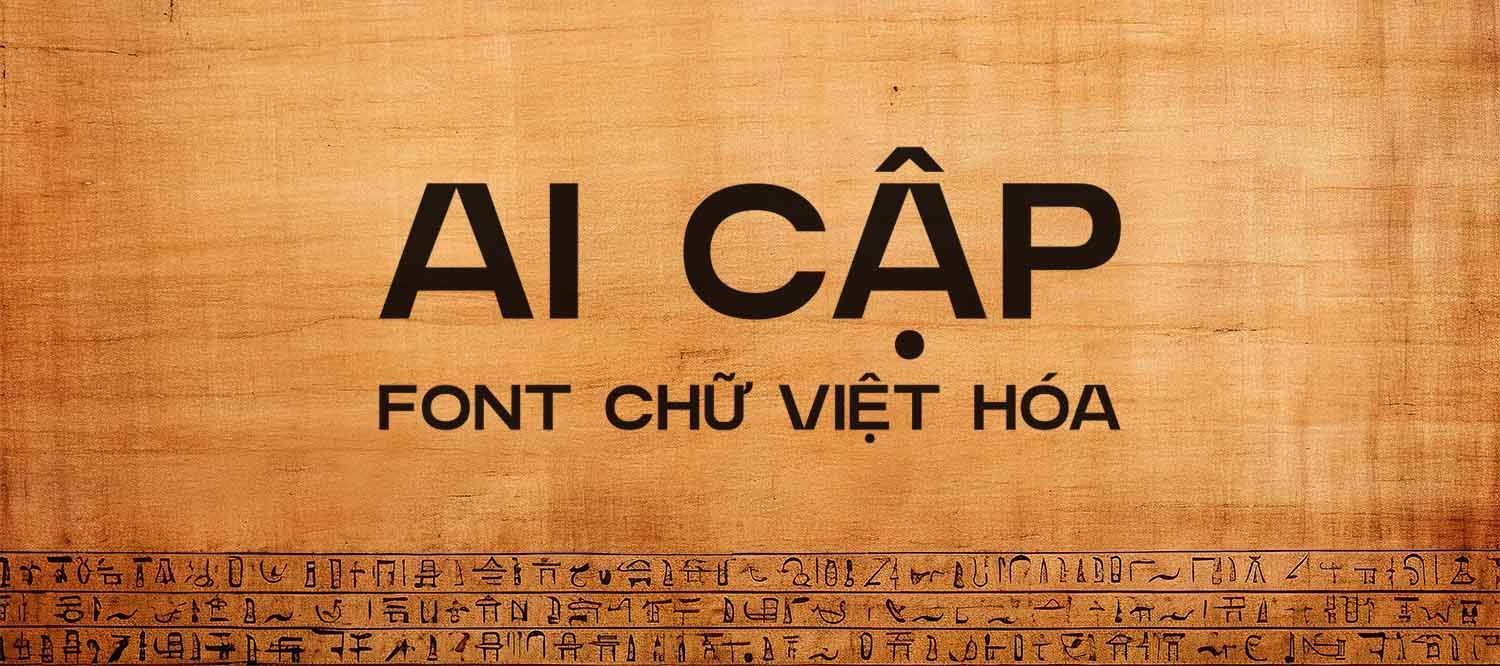
![[Tải Xuống] 8 Font Chữ Ai Cập Việt Hóa Mới Nhất 2025](https://cdn.s99.vn//cloud/Ybaxaa0q71KRf4B-.jpeg)
Font chữ Ai Cập là nhóm font lấy cảm hứng từ văn minh Ai Cập cổ đại, nơi nổi tiếng với hệ thống chữ tượng hình (hieroglyphics), hình khối mạnh mẽ, và những hoa văn trang trí đậm tính biểu tượng. Trong thiết kế hiện đại, font kiểu Ai Cập thường mang nét trang trí cổ kính, uy nghi và huyền bí.
Cũng cần phân biệt rõ với thuật ngữ “Egyptian” trong ngành typography, vốn là tên gọi khác của slab serif, kiểu chữ có chân vuông và dày, không nhất thiết liên quan đến Ai Cập về mặt văn hóa. Trong bài viết này, “font chữ Ai Cập” được hiểu là các font gợi nhắc đến nét đẹp cổ đại Ai Cập, đã được Việt hóa để dùng trong thiết kế tiếng Việt.
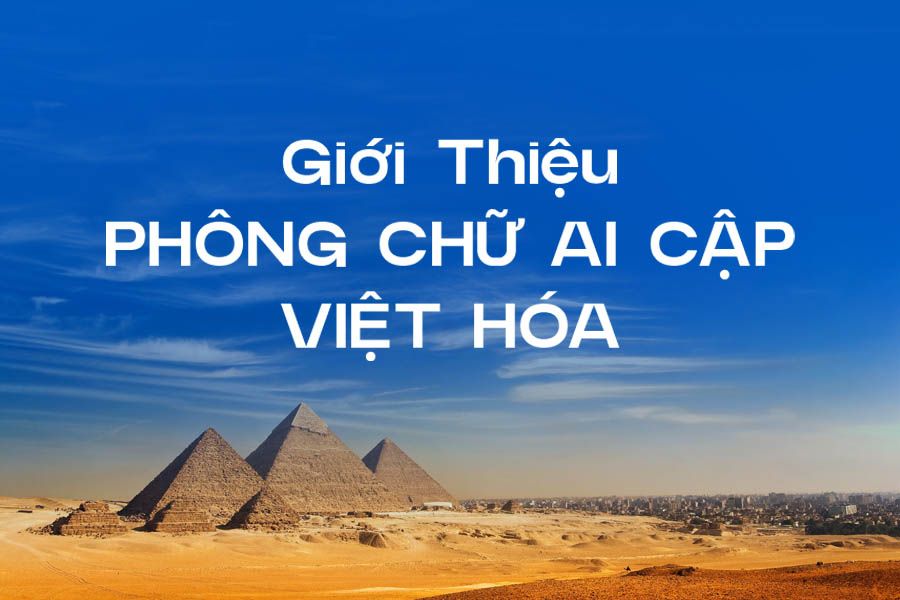
Nếu bạn đang tìm kiếm các font chữ Ai Cập Việt hóa mang đậm cảm hứng cổ đại, phù hợp để sử dụng trong các thiết kế poster lịch sử, sách cổ, game huyền thoại hoặc các dự án branding phong cách văn minh xưa – dưới đây là 8 lựa chọn font miễn phí, đã được Việt hóa hoàn chỉnh cho năm 2025.
Mô tả: SVN Nubya là font display mang phong cách font chữ Ai Cập hiện đại, với các đường nét đậm – mảnh tương phản, gợi cảm giác thư pháp Ả Rập cổ. Kiểu dáng uy nghi và phóng khoáng tạo nên một tổng thể bí ẩn, mạnh mẽ, rất phù hợp cho tiêu đề poster cổ đại, ấn phẩm tôn giáo hoặc các dự án thiết kế mang màu sắc thần thoại.
Mô tả: Tuy có tên gốc là Nhật Bản, font này khi Việt hóa lại sở hữu bố cục vuông vức, đều đặn, mang nét chạm khắc gỗ truyền thống – tương đồng với nhiều yếu tố tạo hình trong font chữ Ai Cập cổ đại. Đây là lựa chọn phù hợp cho các thiết kế phục dựng văn minh phương Đông, hoặc kết hợp trong các dự án lịch sử giả tưởng.
Mô tả: TH Lịch Sử 2 là font slab serif mạnh mẽ, thiết kế dựa trên hình khối vững chắc và cấu trúc chữ cổ điển, dễ gợi liên tưởng đến kiến trúc Ai Cập như kim tự tháp, tượng thần. Đây là một trong những font chữ Ai Cập Việt hóa lý tưởng cho các dự án game lịch sử, bìa sách khảo cổ hoặc các ấn phẩm bảo tàng.
Mô tả: Với đường nét sắc sảo và thanh mảnh, MTD Briliants Typeface tái hiện tinh thần vương giả, uy nghiêm trong các lăng mộ hoàng gia Ai Cập. Kiểu chữ cao, đầu nét nhọn nhẹ và thân chữ thanh thoát làm cho nó trở thành font chữ Ai Cập cao cấp, thích hợp với thiết kế logo, thiệp mời sang trọng hoặc bìa sách cổ tích huyền bí.
Mô tả: LNTH Daybreaker mang hơi thở của chữ khắc đá, nét đứt đoạn mô phỏng kỹ thuật khắc gỗ cổ xưa. Dù lấy cảm hứng từ lễ hội phương Đông, nhưng nhờ kết cấu chữ cổ và hình thái thủ công, font này vẫn rất phù hợp khi dùng như một font chữ Ai Cập cách điệu trong các thiết kế dân gian, cổ tích hoặc game thần thoại.
Mô tả: SVN Bestagrach là font serif có độ tương phản vừa phải giữa các nét, tạo nên cảm giác sang trọng như một bản khắc đá quý tộc thời Ai Cập cổ. Đây là font tuyệt vời cho các thương hiệu cao cấp muốn kết hợp yếu tố font chữ Ai Cập hiện đại vào bộ nhận diện thương hiệu.
Mô tả: Với thân chữ vuông, chân chữ to bản và các nét ngang dày, TH Juggernaut mang lại cảm giác của tấm bia khắc đá khổng lồ trong các ngôi đền Ai Cập. Đây là một trong những font chữ Ai Cập Việt hóa phù hợp nhất để dùng trong tiêu đề, poster hoặc giao diện cổ điển mang màu sắc thần thoại.
Tác giả gốc: Pixel Surplus
Việt hóa: S99.vn
Mô tả: TH Sawadikap là font trang trí có nét uốn mềm mại và chi tiết cong nhẹ ở đầu chữ, tuy lấy cảm hứng từ kiểu Thái cổ, nhưng nhờ yếu tố tạo hình tương tự chữ tượng hình và hoạ tiết Ai Cập, nó hoàn toàn có thể sử dụng như một font chữ Ai Cập biến tấu trong các thiết kế cổ tích, truyền thống, hoặc văn hóa giả tưởng.
Tác giả gốc: Naulicrea
Việt hóa: S99.vn
Mỗi font đều mang trong mình một câu chuyện thị giác: có font tái hiện hình ảnh khắc đá uy nghi trong các đền đài cổ, có font lại mềm mại, thanh lịch như chữ khắc trên giấy cói. Nhờ đó, các dự án như poster phim cổ trang, sách lịch sử, thương hiệu mỹ thuật hay game thần thoại đều có thể tận dụng linh hoạt.